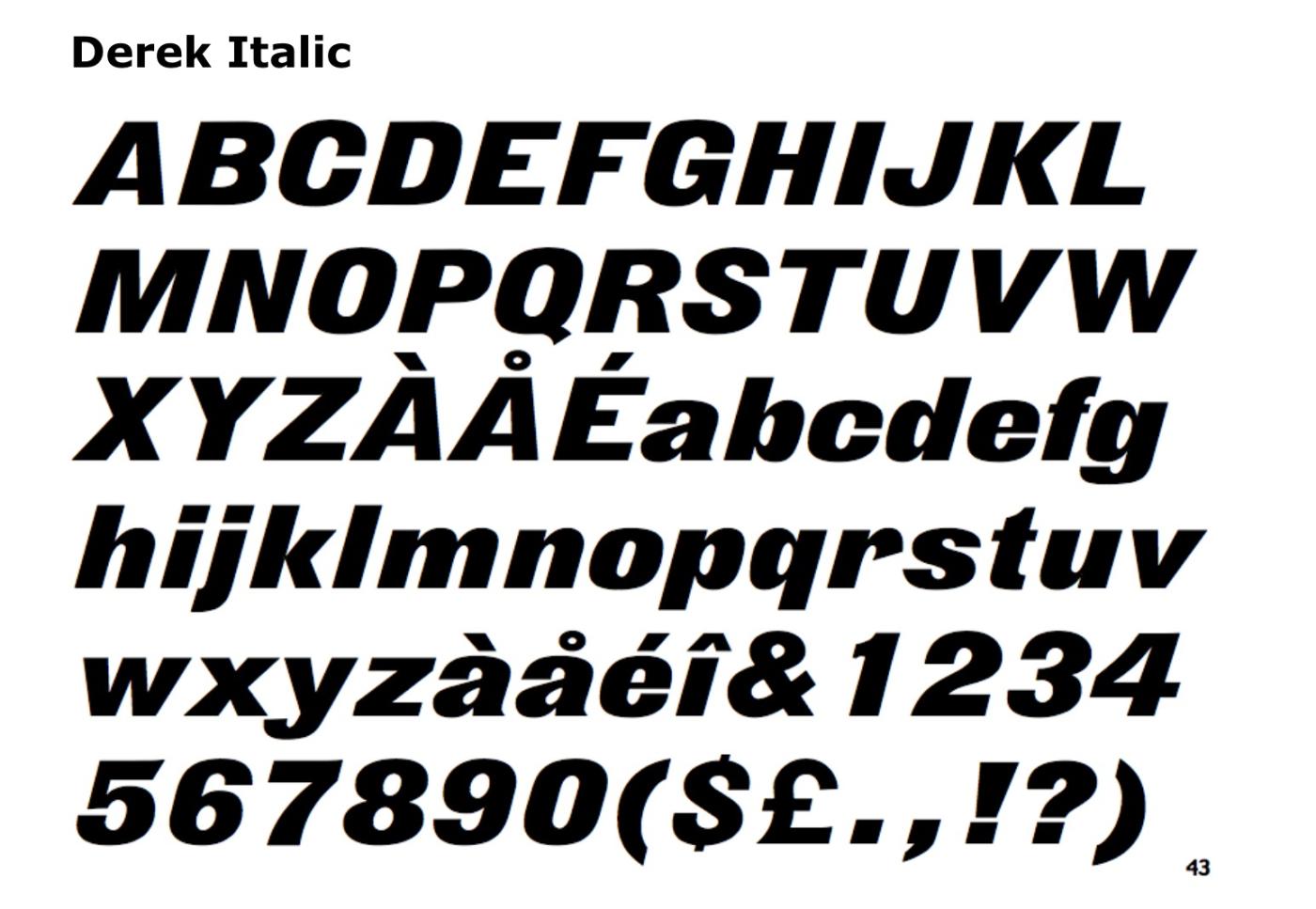
Zeitschriften-Titel-Font (Stern, 1970er)
Aus welcher Schrifttype wurde der Titel „stern magazin“ der deutschen “Stern“-Illustrierten in den 70er Jahren ff. gesetzt? Ich meine, mich zu erinnern, dass es der Font „Etrusker“ war. Den kannte ich aus damaligen Letraset-Katalogen, denn er war - so meine ich - auch als Anreibeschrift auf den Letraset-Rubbelbuchstaben-Bögen käuflich erhältlich. Seltsamerweise wird mir dieser Font aber bei keiner Google-Suche unter „Font Etrusker“ angezeigt. Auch bei „Fontshop.de“, einem der größten und seriösesten Schriftenhändler, war die „Etrusker“ nicht zu finden. Als ob dieser Font aus dem Gedächtnis der Menschheit gelöscht und ausradiert wurde. Gibt es hier eine große und ignorante Vergesslichkeit?
Ich habe über einen Fontfinder eine ähnliche Schrift gefunden, die „Derek Italic“. Sie sieht aber nach meinem Dafürhalten eher wie eine billige „Raubkopie“ des Originals „Etrusker“ aus, denn sie weist einige unschöne und untypische Abweichungen auf. Vielleicht sind da womöglich Rechte aufgekauft worden und die ehemalige „Etrusker“ wurde in „Derek Italic“ umgemodelt. Aber so ganz überzeugend wäre eine solche Theorie für mich auch nicht …
Die Derek ist keine billige Raubkopie, sondern die Digitalisierung der »Fette Kursiv-Grotesk«, auch bekannt als »Doric Italic«, durch Compugraphic, ca. 1982.
Die Original stammt wohl schon aus dem 19. Jahrhundert (Fette Cursiv-Grotesque) und wurde damals schon von unzähligen Anbietern aufgelegt. Und dann kamen im 20. Jahrhundert noch die Varianten im Fotosatz und Digitalsatz dazu. Etrusco (nicht Etrusker) war der Name bei Nebiolo in Italien. Da gibt es auch eine frische Neuauflage ☞ https://www.italiantype.com/etrusco-now
In den alten Letraset-Katalogen wurde dieser Font als „Etrusker“ geführt - würde mich wundern, wenn mir da meine Erinnerung aus der Jugend eine Streich spielen würde. Ich bin jahrelang bei SPITTA&LEUTZ am Hohenzollerndamm in Berlin ein- und ausgegangen, um mir die Letraset-Bögen zu kaufen, mit denen ich Monat für Monat die Headlines für eine Zeitschrift rubbelte. Da haben sich die Schriftnamen bei mir tief eingeprägt und ich könnte sie aus dem Stand singen und tanzen … 😉
Und die „frische Neuauflage“ »Etrusco New« ist auch nur eine sterile und überperfekte moderne Version, der der unperfekte und etwas „liederliche“ Charme des Originals leider gänzlich fehlt - meiner Meinung nach …
Stimmt, dieser Font scheint tatsächlich das Original zu sein. Warum dieser Klassiker unter so vielen verschiedenen Namen existiert, ist seltsam.
Dass der Font auf jeden Fall „Etrusker“ geheißen haben muss, ist ja schon daran erkennbar, dass die Neuauflage  unter „Etrusco“ geführt wird, also ist das schon mal vom Namen her bewiesen. Und in den 70ern und 80ern hatte ich eben sehr viel und sehr intensiv unmittelbar und analog als „Hardcore-Rubbelschriften-Nutzer“ über Jahre damit zu tun. Ich habe das alles noch regelrecht fotografisch im Gedächtnis. Es gab neben Letraset übrigens auch „LetraGraphica“-Rubbelbögen! Und es gab diese Letraset-Kataloge, die man für eine Schutzgebühr von 5 DM kaufen konnte. Und es gab auch Konkurrenz-Rubbelschriften-Anbieter anderer Hersteller. Alles Erinnerungen, als ob es gestern gewesen wäre. „Etrusker“ hat sich nun mal bei mir eingebrannt, sonst könnte ich nicht auch mal eben so die Hersteller aus dem FF herunterbeten.
Das mag für Italien zutreffen, aber ich behaupte, dass es da vermutlich eine Eindeutschung gegeben haben könnte, so dass diese Schrift bei uns in den Katalogen eben „Etrusker“ genannt wurde. Ich habe lediglich diesen Namen in Erinnerung, nicht „Etrusco“. Aber sei‘s drum. Einer dieser alten Letraset-Kataloge liegt mir nicht mehr vor und vielleicht hatte ich diese Schrift unter diesem Namen ja auch in einem anderen Katalog gesehen.